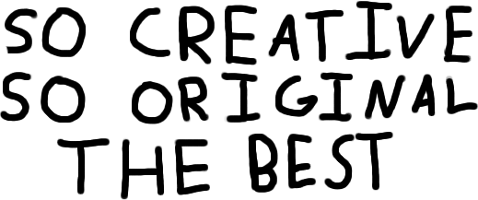
[Q] Czy to czcionka?
To nie jest czcionka. Ktoś to ręcznie napisał.
takie same literki różnią się od siebie.
A no przecież, a znasz może jakąś czcionkę, która wygląda podobnie?